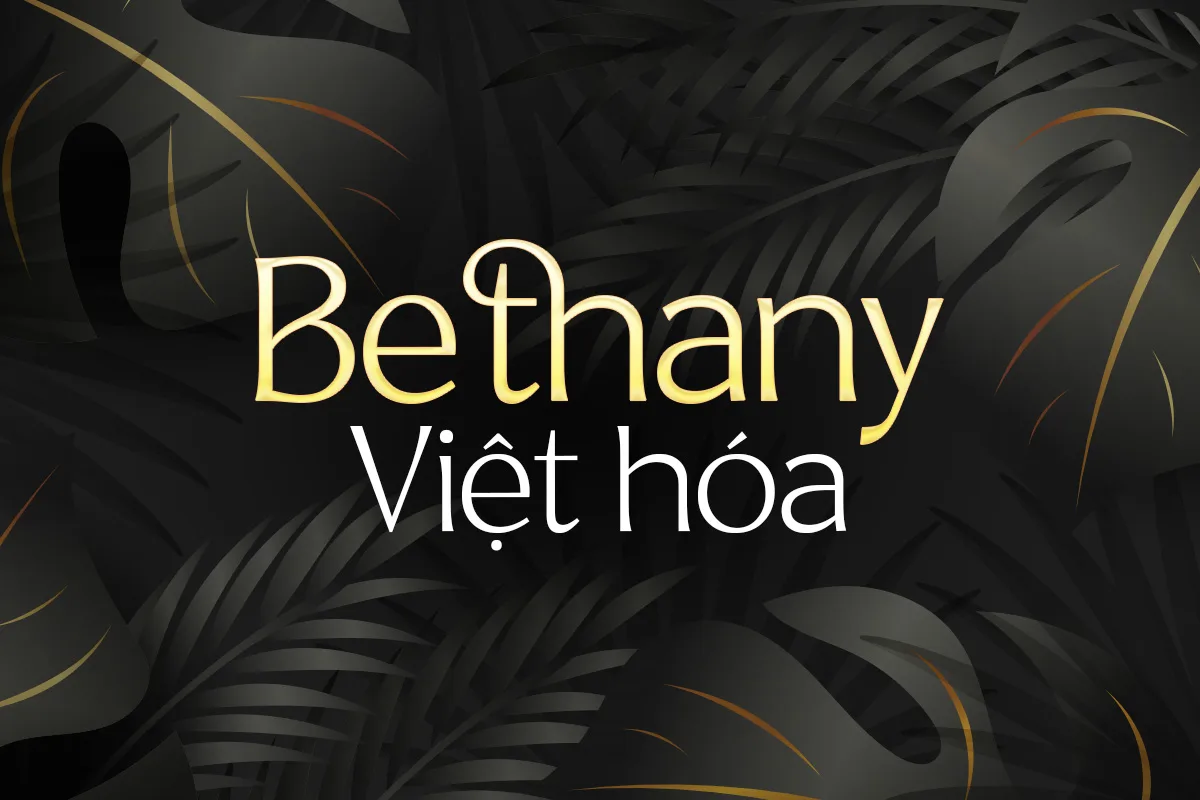
DVN Bethany Việt hóa – Font chữ uyển chuyển nhẹ nhàng và thanh thoát
DVN – Bethany là một kiểu chữ serif mang đậm vẻ thanh lịch và lãng mạn, được thiết kế với những đường cong mềm mại và độ tương phản vừa phải. Font gợi cảm giác hoài niệm, gắn liền với những câu chuyện điện ảnh, những trang tiểu thuyết hay poster nghệ thuật.
Với đặc trưng chữ cái uốn lượn duyên dáng, DVN – Bethany mang đến không khí mộng mơ, cổ điển nhưng vẫn tinh tế và hiện đại. Đây là lựa chọn lý tưởng cho:
• Poster phim, bìa sách, album âm nhạc
• Thiệp mời cưới, tạp chí thời trang
• Các dự án thiết kế mang hơi thở retro – vintage hoặc narrative design
Khi sử dụng, DVN – Bethany không chỉ là một font chữ, mà còn như một lời thì thầm của ký ức, đưa người xem chạm đến những xúc cảm nhẹ nhàng và sâu lắng.